Tironische Noten
Römisches Kurzschriftsystem. In der Paläografie auch als »Tironiana« bezeichnet. Im ersten vorchristlichen Jahrhundert von Marcus Tullius Tiro (um 103–4 v.Chr.) entwickelt. Tiro war in seiner Jugend Sklave im Hause des römischen Dichters, Redners und Staatsmanns Marcus Tullius Cicero (106–43 v.Chr.) gewesen, wurde aber dank seiner Intelligenz und Gelehrigkeit bald zu dessen Privatsekretär und schließlich sogar aus der Sklaverei entlassen.
Im Rang eines professionellen Schreibers, damals eine Stellung mit sehr hohem sozialen Ansehen, notierte Tiro hauptsächlich die Protokolle der in Volksversammlungen oder vor dem Senat gehaltenen Reden römischer Politiker. Tiro und Cicero blieben einander zeitlebens freundschaftlich verbunden und nach dem Tod seines berühmt-berüchtigten Mentors verfaßte Tiro die erste Biographie über Cicero. Diese ist zwar nicht original erhalten, wurde jedoch von dem altgr. Schriftsteller Plutarch (um 45–125) als Hauptquelle für dessen »Vita Ciceronis« oft zitiert. Tiro war auch der erste Herausgeber von Ciceros Reden und Briefen.
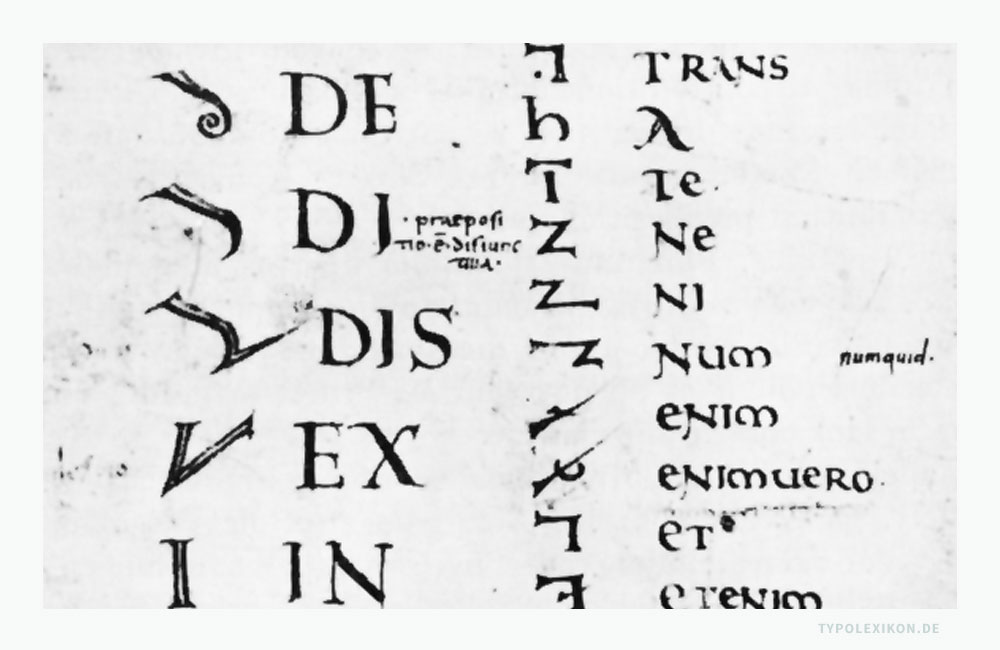
Marcus Tullius Tiros bedeutender Beitrag zur westeuropäischen Schriftgeschichte ist seine Verbesserung eines lediglich rudimentär überlieferten, aus dem zweiten vorchristlichen Jahrhundert stammenden Tachygraphiesystems des Dichters Quintus Ennius (geboren 239 v.Chr. in Rudiae, Kalabrien, gestorben 169 v.Chr.). Ennius soll übrigens die beiden Abbreviaturen M für Mille (Tausend) und C für Centum (Hundert) (siehe Römische Zahlen) erfunden haben, wie Isidor von Sevilla um 620 in seiner zwanzigbändigen Enzyklopädie des gesamten Wissens jener Zeit »Originum seu etymologiarum libri XX« berichtet.
Der erste Nachweis der »notae Tironianae« ist aus dem Jahr 63 v.Chr. überliefert, als Tiro die Rede des jüngeren Cato gegen den putschenden Catilina mitschrieb. Tiro hat, um das gesprochene Wort quasi »synchron« festzuhalten, alle Möglichkeiten zur vereinfachten Darstellung ausgeschöpft; in systematischer Kombinatorik von bereits üblichen mit neuen Abbreviaturen, von Graphemkürzungen mit Strichen, Punktierungen und Durchkreuzungen entwickelte er ein 4.000 Zeichen umfassendes Repertoire, das von seinen Schülern Vipsanius Filagrius und Aquila noch erweitert wurde. Seneca verfaßte ein erstes kommentiertes Lexikon mit 5.000 unterschiedlichen Noten.
Diese spezielle Schreibkunst nach Tiro wurde in den römischen Schulen gelehrt und war im Altertum weit verbreitet. Auch Caesar hat sie beherrscht. Die frühchristlichen Konzilien wurden ebenso in »Tironischen Noten« protokolliert wie die Predigten des Theologen und Philosophen Augustinus von Hippo (um 354–430).
Die sogenannten »Notare« hatten auch ihren eigenen Heiligen, Cassian von Imola (gestorben um 304), der als Schriftenlehrer in Rom während der Christenverfolgungen unter Diokletian von seinen Schülern erstochen worden war – mit Schreibgriffeln.
Im Mittelalter umfaßte Tiros Schrift über 13.000 – auswendig zu lernende – Noten und wurde vor allem in klösterlichen Skriptorien gepflegt, wie etwa im Martinskloster zu Tours, das bis zur Mitte des 9. Jahrhunderts eine der wichtigsten Gelehrtenschulen des karolingischen Kulturraumes beherbergte; das Korrigieren, Exzerpieren und Kommentieren waren typische Tätigkeiten, bei denen die »Tironiana« zum Einsatz kamen.
Aus offiziellen Urkunden (siehe Diplomatik) der Hofkanzleien wurden sie erst um das Jahr 1100 verbannt. Die Besinnung auf die Kultur der Antike zu Beginn der Renaissance führte zur Wiederbelebung der Tironischen Noten durch den deutschen Humanisten Johannes Trithemius und in der Folge auch in der Typografie zur Ausbildung eines umfangreichen Repertoires an Kürzeln, Schriftkürzungen und Abbreviaturen.
Mit fortschreitender Entwicklung der eigentlichen Stenographie ausgehend von England verloren die Tironischen Noten ab dem 17. Jahrhundert ihren praktischen Wert. Sie sind heute nur noch für die Schriftgeschichte von Bedeutung. Um das Jahr 2000 hat der deutsche Paläograph Martin Hellmann das komplette Tironische Zeicheninventar in digitaler Form erschlossen; für die Wiedergabe der Tironiana entwickelte Hellmann den elektronischen Zeichensatz »Liutramnus«, benannt nach einem Schreibmönch im Skriptorium von Tours. 1) 2) 3) 4)
| ↑1 | Literaturempfehlung: Boge, Herbert: Griechische Tachygraphie und Tironische Noten. Ein Handbuch der antiken und mittelalterlichen Schnellschrift, Berlin 1973. |
| ↑2 | Literaturempfehlung: Schiaparelli, Luigi: Tironische Noten in den Urkunden der Könige von Italien aus dem 9. und 10. Jahrhundert, Archiv für Stenographie 57, 1906. |